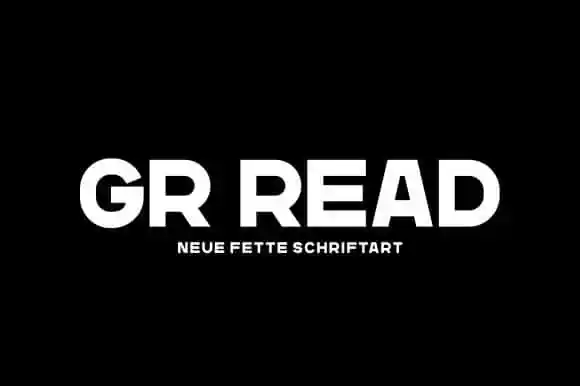
GR Read One Sans Serif Font – Download Grátis
Aproveite a novidade com a GR Read One Sans Serif Font, uma elegante tipografia sans serif lançada pela Garisman Studio. Esta fonte pronta para uso é perfeita para designs de cabeçalho que valorizam uma temática moderna e sóbria. Inspirada nos headlines atuais encontrados em postais ou revistas, essa fonte traz um estilo firme e extremamente moderno à sua criação. Seu forte display e linhas limpas dão ao texto uma presença mais marcante e característica. A GR Read One Sans Serif é o ideal para quem busca uma tipografia sofisticada e versátil para expressar seu design de maneira atraente. Não perca tempo, teste essa fonte em seus próximos projetos!